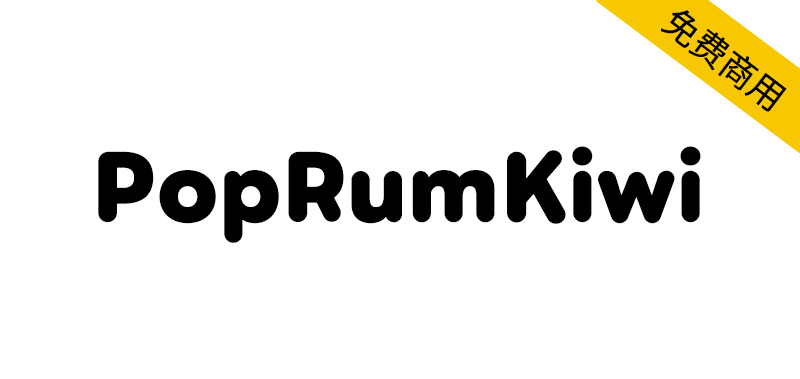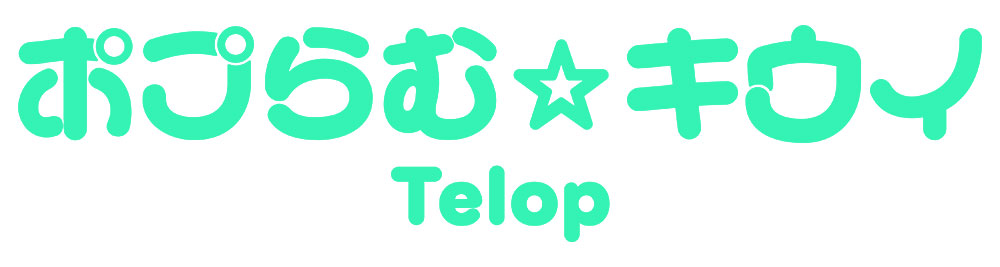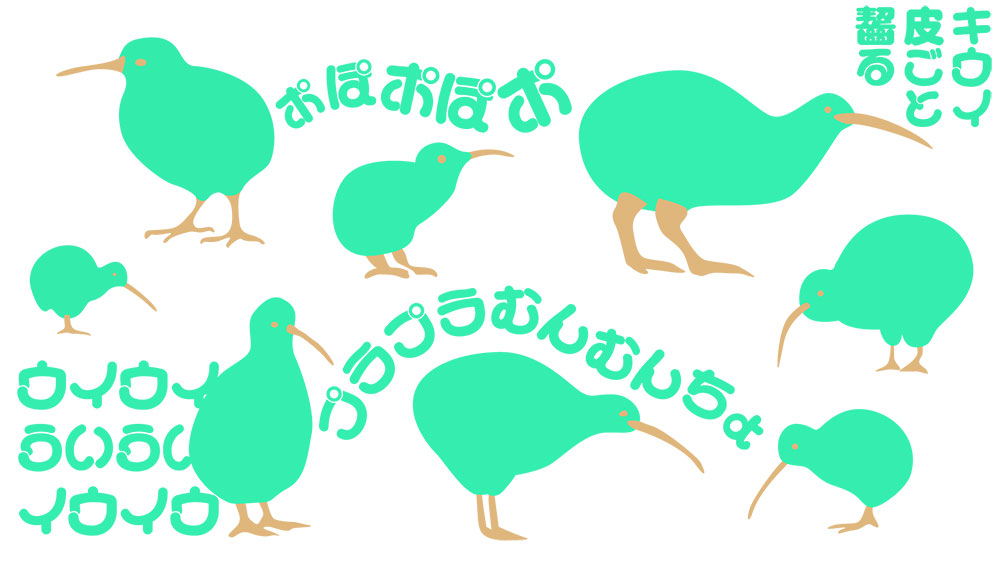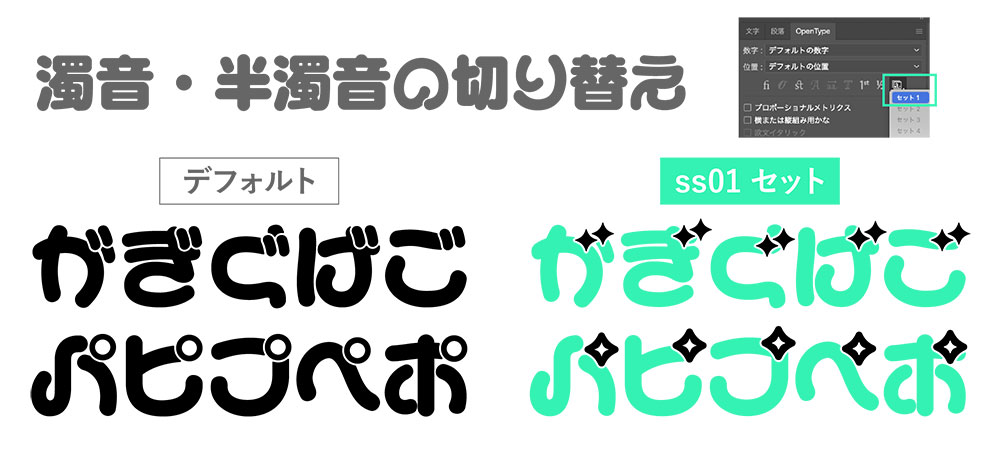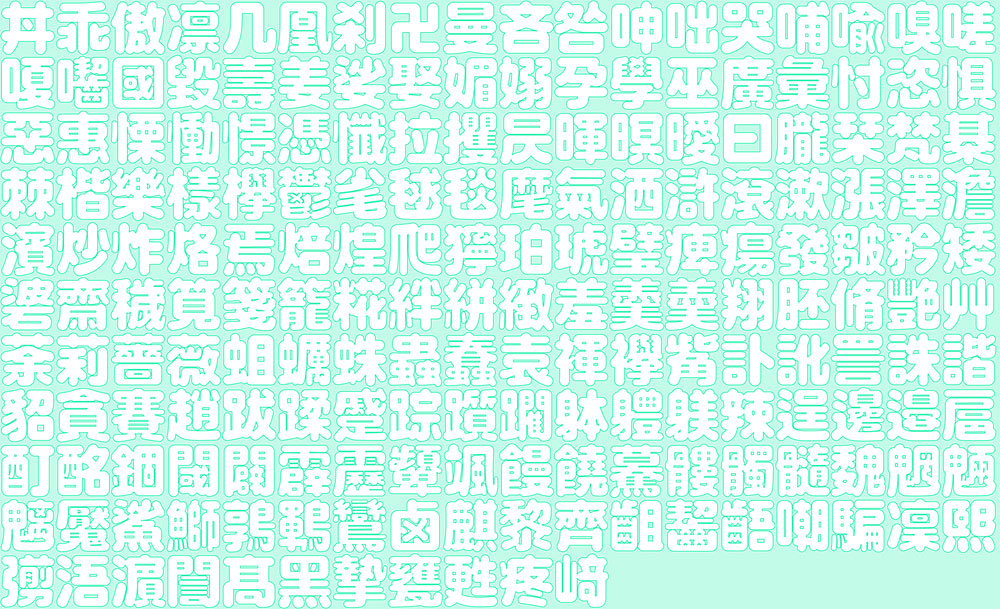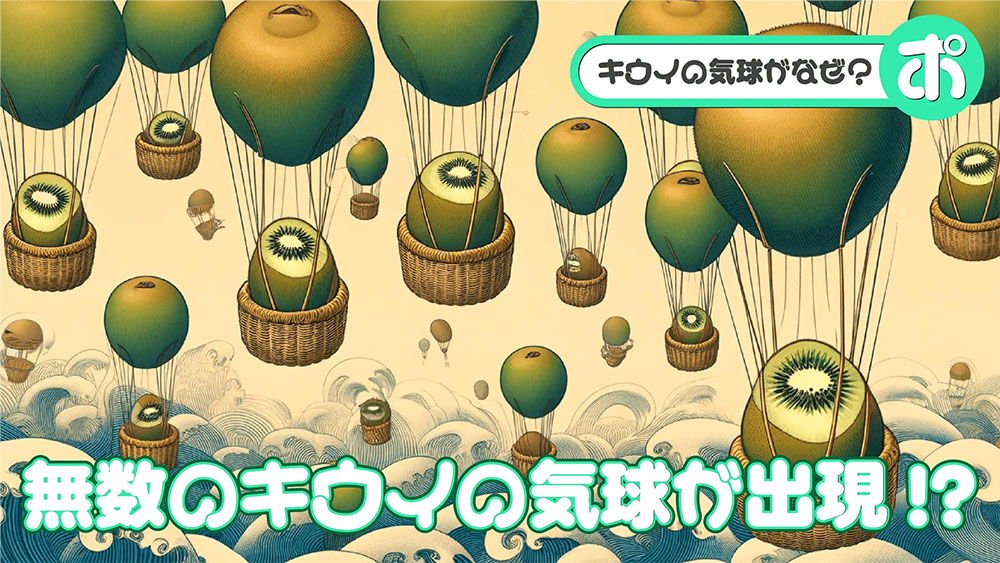
PopRumKiwi(ポプらむ☆キウイ)是一款基于LINE Seed(ExtraBold)字体进行圆角处理的日系圆体字体,LINE Seed与M+fonts或思源黑体这类仅需单一滤镜即可实现圆角效果的字体不同,LINE Seed字体浑身散发着"别以为开源字体就能随便衍生出圆角版本"的气场。PopRumKiwi(ポプらむ☆キウイ)原本并未打算做到这种程度,但一旦着手就变得骑虎难下,最终耗费大量时间精力,成功为其打造出了圆角版本。
由于徒手绘制全部字形实在太费功夫,其中的汉字和西文部分借用了LINE Seed(ExtraBold)的骨架。为避免许可证混淆,将字体命名为 PopRumKiwi(ポプらむ☆キウイ),本字体作为LINE Seed的衍生作品,遵循SIL Open Font License 1.1开源协议。
收录汉字数量为:JIS第一级汉字 + JIS第二级汉字(184字),IBM扩展汉字(34字)。对于Illustrator用户,可以切换浊音和半浊音显示。